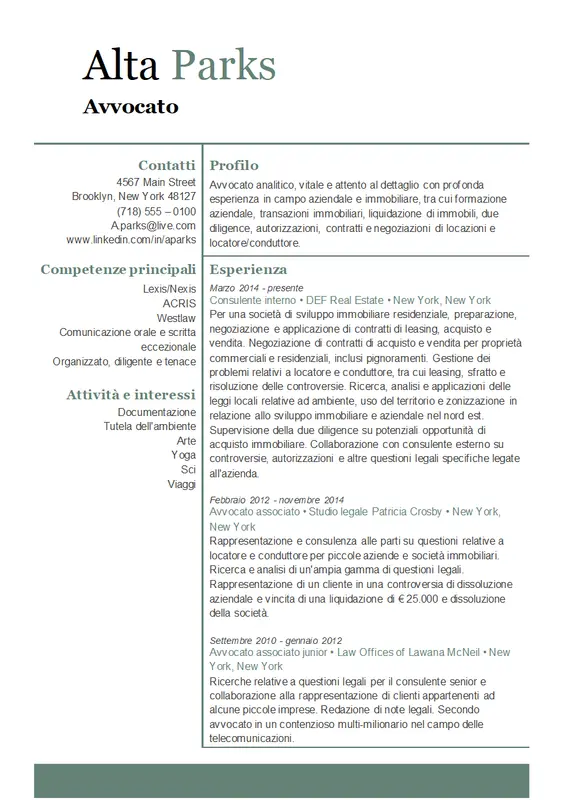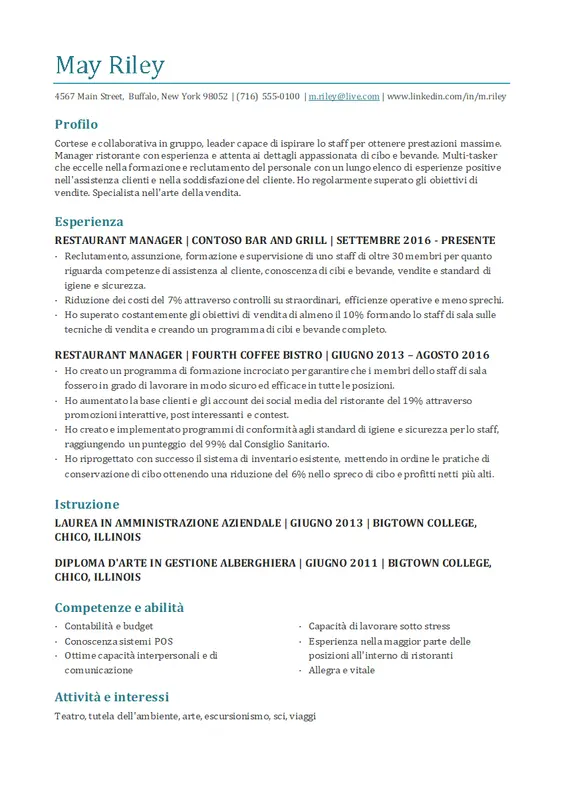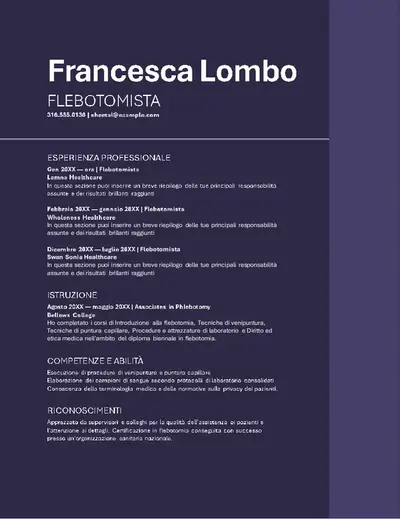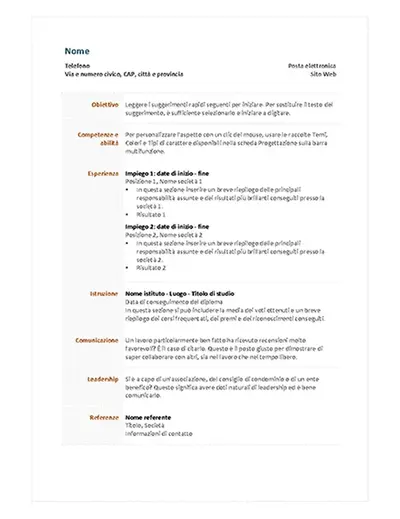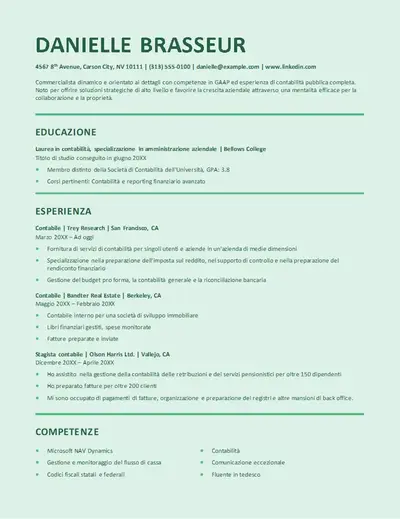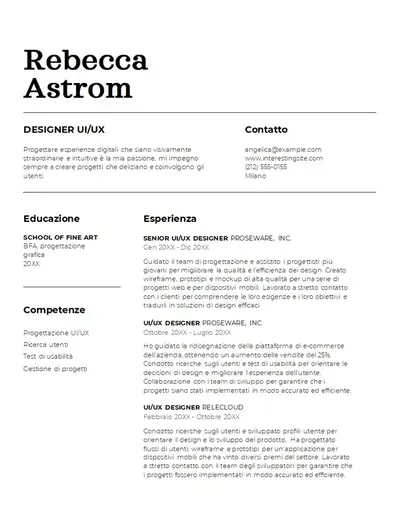
La scelta del tipo di carattere giusto per il curriculum è uno dei modi più efficaci per fare una buona prima impressione. I tipi di carattere possono comunicare credibilità e personalità, supportare la professionalità e perfezionare un curriculum per riflettere l'attenzione ai dettagli.
Inizia a creare un curriculum ben progettato con suggerimenti pratici sulla scelta di stili e dimensioni di carattere appropriati. Scopri come creare una chiara gerarchia di tipi di carattere, applicare la formattazione in modo coerente e creare un curriculum raffinato in Microsoft Word.
I sei migliori caratteri di curriculum per qualsiasi candidatura di lavoro
Il miglior tipo di carattere per il curriculum non si limita a fare bella figura sulla pagina. La scelta del carattere modella il modo in cui un curriculum viene letto, classificato e ricordato. Ecco i migliori font dall'aspetto professionale perfetti per scrivere un curriculum, tutti disponibili in Microsoft Word.
1. Font Calibri
Un moderno font sans serif, Calibri è diventato il gold standard aziendale. Semplice da leggere, Calibri trasuda professionalità e autorità. Con stili audaci e chiari, questo tipo di carattere sans serif è facilmente adattabile per adattarsi a qualsiasi impressione. Ideale per professioni come quella legale, finanziaria e sanitaria, Calibri si adatta a qualsiasi ruolo in cui un aspetto pulito e professionale è la priorità.
2. Carattere Garamond
Un classico font serif, Garamond è una scelta affidabile nell'editoria professionale e nei documenti formali. Il tipo di carattere è facile da leggere in dimensioni ridotte, conferendo al curriculum un aspetto autorevole e raffinato. Garamond è una scelta forte per ruoli nel mondo accademico, nell'editoria, nel diritto e nelle posizioni esecutive in cui è apprezzata una presentazione tradizionale e ad alta credibilità.
3. Carattere Montserrat
Montserrat porta un aspetto pulito e accessibile a un curriculum. Un carattere tipografico ideale per la pubblicità stampata e la segnaletica stradale urbana, Montserrat è una scelta naturale per i curriculum in campi creativi, benessere e immobiliari. Questo tipo di carattere sans serif ha un aspetto audace pur essendo estremamente chiaro e leggibile.
4. Carattere Candara
Candara è un'opzione sottilmente elegante che sembra raffinata senza essere eccessivamente formale. Facile da leggere con uno stile distintivo, questo font si adatta a curriculum meno pesanti come un formato curriculum combinato e funziona particolarmente bene per stage, software e ruoli IT.
5. Carattere Cambria
Cambria è un tipo di carattere serif tradizionale ed equilibrato che trasmette affidabilità e professionalità. Progettato per Facile lettura su schermo (opens in a new tab) in piccole dimensioni di testo, Cambria è un'opzione sofisticata che si adatta a qualsiasi curriculum. Questo tipo di carattere serif è adatto a ruoli di gestione, risorse umane e leadership ed è un'opzione ideale per i curriculum di ingegneria e architettura, poiché il design supporta simboli matematici e scientifici.
6. Carattere Aptos
Aptos è il tipo di carattere predefinito in Microsoft Word e Microsoft 365 che bilancia lo stile contemporaneo con una solida leggibilità per creare un curriculum chiaro e leggibile. Progettato per la leggibilità su schermi moderni con un tono più caldo e neutro, Aptos (opens in a new tab) è un tipo di carattere sans serif flessibile che si adatta ai titoli e al corpo del testo. Questo stile di carattere contemporaneo è particolarmente adatto per applicazioni tecnologiche, sanitarie e gestionali.
7. tipo di carattere Arial
Arial è un tipo di carattere sans serif semplice e lineare che conferisce a un curriculum un aspetto professionale e facile da interpretare. La sua flessibilità lo rende una scelta pratica per i curricula in tutti i ruoli lavorativi e le fasi della carriera, sia condivisi digitalmente che in formato cartaceo. Questo tipo di carattere pulito e coerente è particolarmente compatibile con le applicazioni aziendali, rivolte ai clienti e incentrate sul business.
Come scegliere un tipo di carattere professionale per il curriculum
Dopo aver selezionato un elenco di tipi di carattere adatti, il passaggio successivo consiste nel trovare la corrispondenza giusta per il domanda di lavoro. La scelta del carattere giusto in base al ruolo lavorativo e al livello di anzianità implica la comprensione delle sfumature culturali e professionali di ciascun settore lavorativo, nonché dell'impressione che deve fare sui potenziali datori di lavoro. Ecco alcune linee guida per aiutarti a trovare il tipo di carattere migliore.
Considerare il ruolo e il livello di lavoro
Diversi ruoli lavorativi e livelli di anzianità possono influenzare la creatività o la formalità di un curriculum, il design e il tipo di carattere. Considera il livello di anzianità del ruolo, entry-level, mid-level o senior, in quanto determina quanta libertà creativa può richiedere la scelta del carattere.
Apri un curriculum in Word, seleziona il testo da aggiornare e usa l'elenco a discesa dei tipi di carattere nella scheda Home per scegliere un nuovo tipo di carattere. Regola le dimensioni del testo usando il campo delle dimensioni del carattere accanto ad esso. Per aggiornare tutti i titoli o il corpo del testo contemporaneamente, fare clic con il pulsante destro del mouse sullo stile pertinente nella raccolta stili e scegliere Modifica. La modifica viene applicata automaticamente in tutto il documento. Per altri modi di modificare e formattare i documenti in Word, esplora editor documenti.